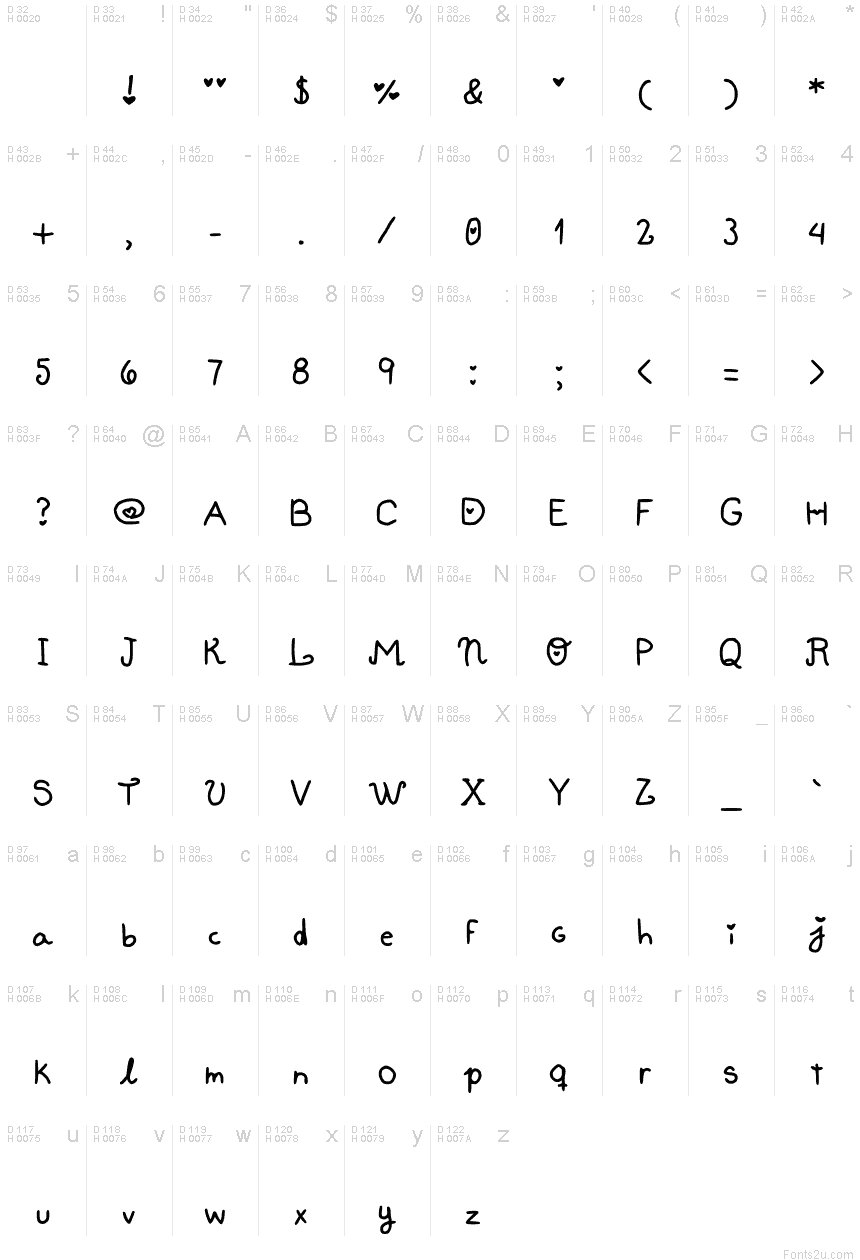
Hobby NeruChan Medium
Una font hecha por una nia de 11 aos. Es perfecta para San Valentn o para una ocasin especial ^^
A font maked by a girl of 11 years old. Is perfect for Valentine's Day ^^